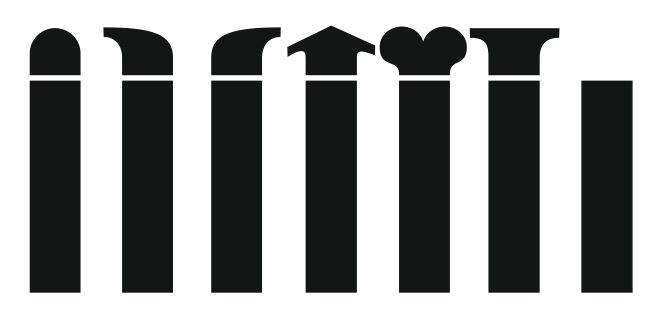
Wie dreht man einen Buchstaben in Fontlap um?
Da hast du gleich mehrere Möglichkeiten:
1. im Glypken-Editor alles markieren, dann Contour - Transform - Flip horizontal und oder Flip vertical-
2. auf den markierten Buchstaben einen Doppelklick, den kleinen Kreis rechts am Auswahlrahmen anfassen und Buchstaben drehen. um ganze 15°-Schritte bei gedrückter Umschalttaste
3. im Font-Fenster, Buchstabe markieren, Tools - Action - da unter Contour Rotate wählen, Drehwinkel eingeben und OK.
Frage zu Kerning im Fontlab.
Hab in Fontlab ein Kerningpaar »is« angelegt – allet schick.
Im Layoutprogramm ist das Kerning falsch.
Wo ist der Fehler? Was mache ich falsch?
Abgespeichert als .otf
Im Layoutprogramm Kerning auf »0« und nicht »optisch« usw. gestellt.
Ich würde zuerst einmal die Vor- und Nachbreiten der Buchstaben so weit richten, dass Kerning wirklich nur bei Problen-Paaren, wie  AV, VA, AW, WA, AT, TA, AY, YA, Vj, WJ, YJ, TJ, LV, LW, LT, LX nötig ist.
Die "Zipfelmütze" des i-Punkts kann durchaus etwas rechts über den virtuellen Kegel heraus ragen, also die Nachbreite nur auf den senkrechten Strich des i beziehen. Auch bei typischen Problembuchstaben wie A, V, Y, T kann man in Bezug auf die äußersten Ecken der Buchstaben gleich mit den Vor- und
Nachbreiten sehr knapp arbeiten, wenn nicht sogar einen Hauch Unterschneiden.
Tipp von mir: öffne dir mal einen der Systermfonts. Nur zum Anschauen darfst du ja jeden Font mal öffnen, da kann dir keiner was. Und da schaure dir ähnliche Buchstaben mal an, z.B. í bei dem dann auch so ein Zipfelchen nach rechts ragt. Auch hier beziehen sich die Zeichen-Breiten nur auf den Stamm des i, nicht auf das nach rechts ausladende diaktitische Zeichen, dass dann ruhig etwas übdben Nachbarbuchstaben ragen kann.
Wo ist der Fehler? Was mache ich falsch?
Aus der Ferne schwer zu sagen. Bedenke, dass es klassisches Tabellen-Kerning und OpenType-Kerning gibt und du letzteres in FontLab generieren lassen musst. Es taucht dann als OpenType-Featur KERN in der OpenType-Palette auf.
Ansonsten hat Catfonts natürlich auch recht: das i (das ich übrigens als langes s lese) braucht gar kein Kerning, sondern nur gute Zurichtung.
Im Layoutprogramm Kerning auf »0« und nicht »optisch« usw. gestellt.
Wenn du das machst, schaltest du jedes Kerning generell ab.
0 = pure Fontmetrik, keinerlei Kerning, auch nicht deines!
"metrisch" = Fontmetrik + Fontkerning  (das willst du zum testen haben, denn da kommt alles aus deinem Font und nichts von Indesign)
"optisch" = Fontmetrik + Indesign-Kerninglogik  (Indesign ignoriert das Fontkerning und berechnet "optimale" Ausgleiche selbst. Gut für schlechte Schriften.)
Also auf Metrisch stellen, und sehen ob sich etwas tut.
Wenn nicht, hat es deine Kerning-Information nicht in deine fertige OTF-Datei geschafft (KERN-Klassen-Generierung) oder das System/Indesign verwendet gar nicht deine aktuelle OTF (sondern eine alte aus dem Cache).
das kerning war richtig. es lag am wert »0« im layoutprog.  :hammer: